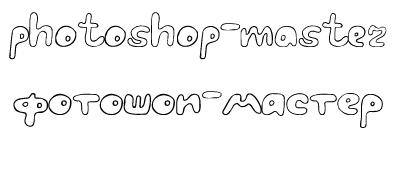
Шрифт - LC Blowzy
Интересный шрифт, который хорошо подходит для работы в фотошопе. Есть поддержка русского языка.
Хорошенький мультяшный стиль *)
необычно)))
Забавный шрифт! Позволяет над собой поработать! Надо воспользоваться
Ухты как оригенально!
супер, особенно с эфектом свечения смотреться будеТ!